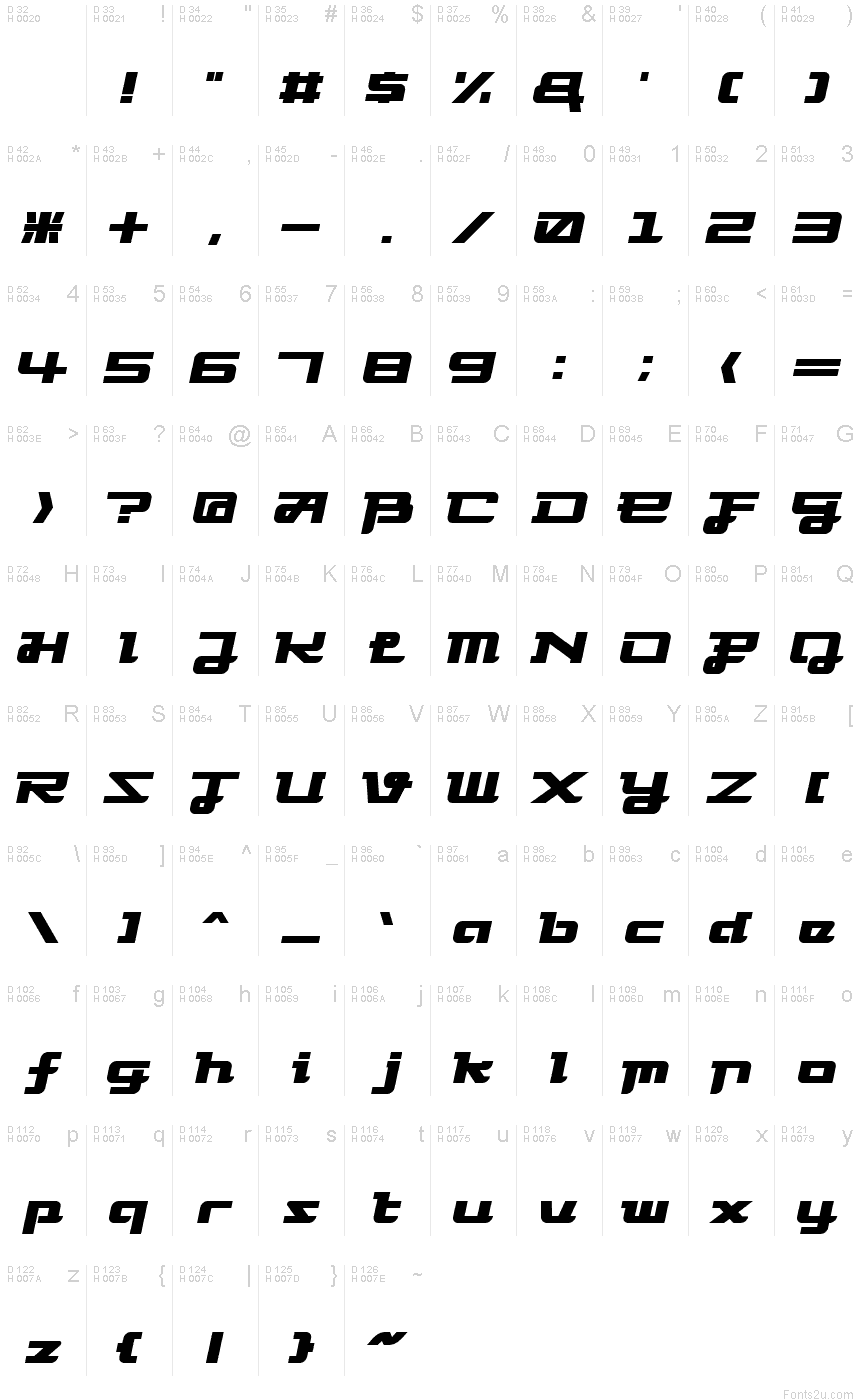
Flyermix Oblique to darmowy, utrzymany w stylistyce retro sci-fi krój displayowy od Flop Design, który mocno osadzony jest w pochylonym klimacie dawnych ulotek. Litery są jednocześnie dynamiczne i masywne; zaokrąglone rogi, głębokie wcięcia i płynne łączenia nadają krojowi charakter gotowego logotypu.
Świetnie sprawdzi się na klubowych ulotkach, plakatach w stylu arcade, okładkach muzycznych, kartach tytułowych czy w znakach graficznych, które potrzebują futurystycznego akcentu z przełomu lat 70. i 80., ale bez przesadnego udziwnienia. Jako darmowy font najlepiej sprawdza się w krótkich nagłówkach, gdzie dzięki pochyleniu oraz szerokim, połączonym kształtom całe słowo tworzy spójną całość graficzną.